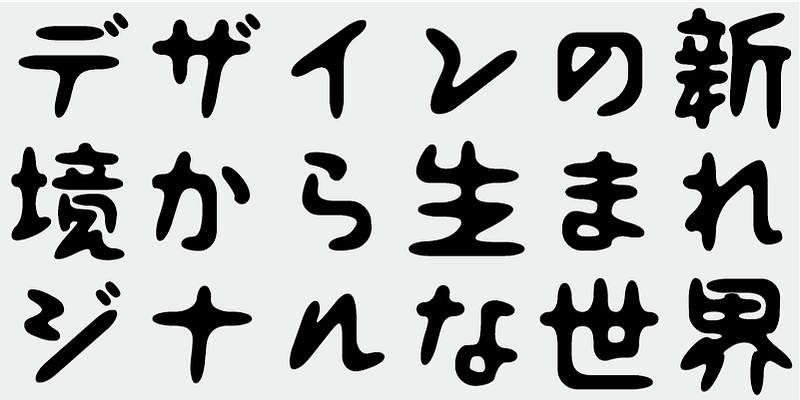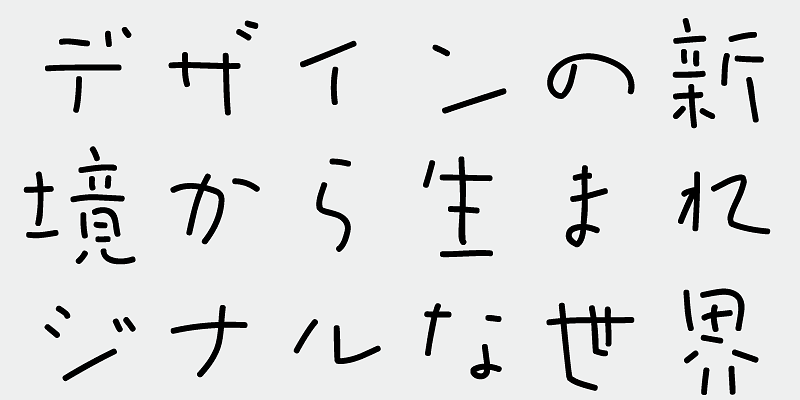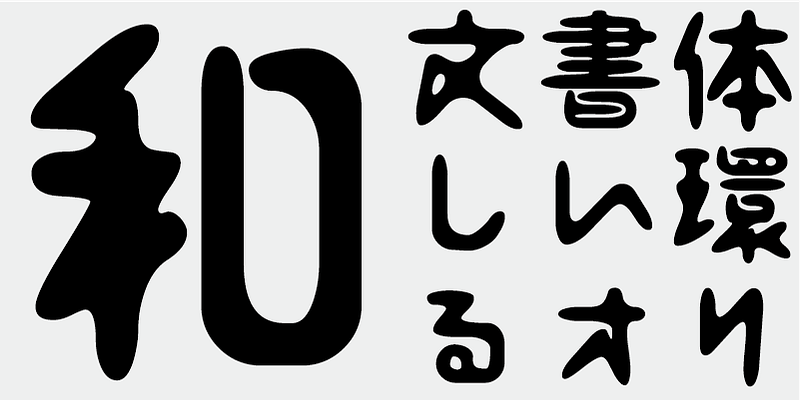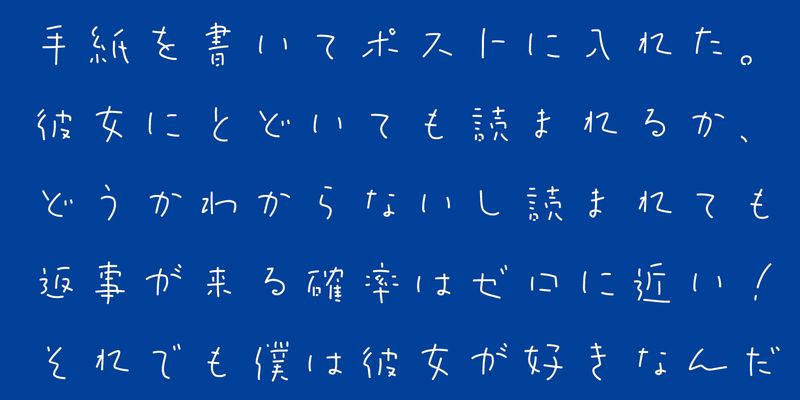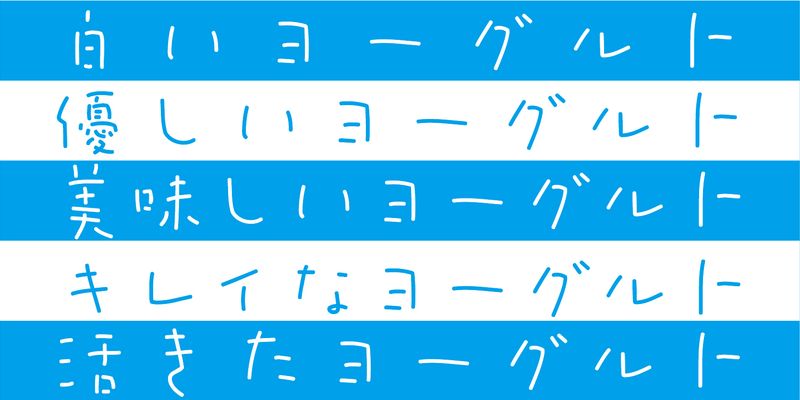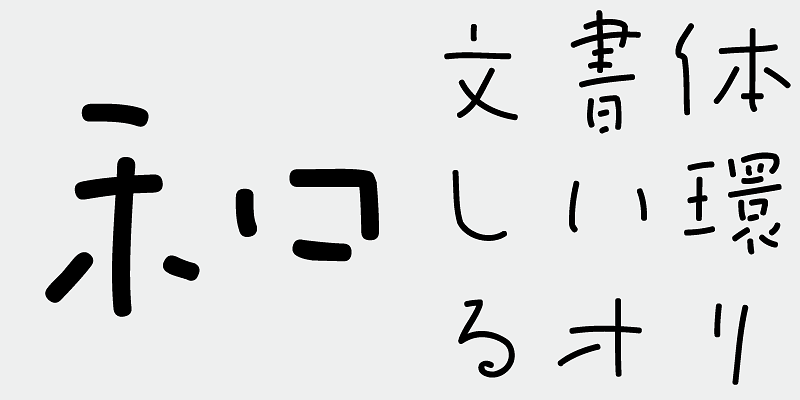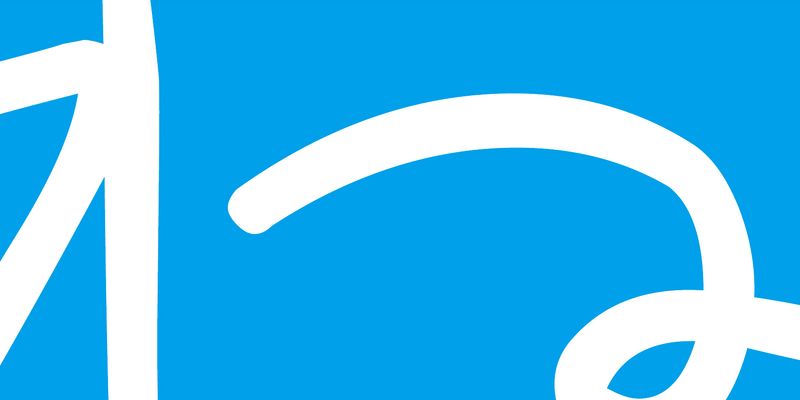
Alors que je concevais un emballage pour un yaourt, j’ai trouvé que le design méritait une police de caractères personnalisée, ce qui a conduit à la conception de cette police inspirée des yaourts.
Cette police comprend les 1 000 principaux caractères kanji choisis dans les tables de fréquence des caractères établis par les sociétés de presse, les maisons d’édition et les instituts de recherche linguistique, ainsi que 206 caractères kana et signes de ponctuation.
Dans la production de polices japonaises d’aujourd’hui, les 7 000 caractères de la norme JIS sont considérés comme essentiels. Mais toutes les polices ont-elles vraiment besoin de 7 000 caractères ? À l’ère de la phototypie, on utilisait beaucoup moins de caractères. FONT1000, un groupe de typographes indépendants, a commencé par se focaliser sur cette simple question. Nous avons sélectionné le minimum de 1 000 caractères kanji (idéographiques) nécessaires pour la composition en japonais et créé activement des polices pour les prendre en charge. Ce jeu de 1 000 caractères kanji a été créé en étudiant des données de fréquence des caractères compilées par des sociétés de presse, des maisons d’édition et des organismes de recherche linguistique, etc. Il comprend également des caractères syllabiques kana et des signes de ponctuation. FONT1000 a été créée en 2001 avec 25 designers et 25 polices de caractères. Aujourd’hui, nous avons 130 polices et comptons désormais près de 40 membres, ce qui permet de travailler sur des polices avec plus de caractères.